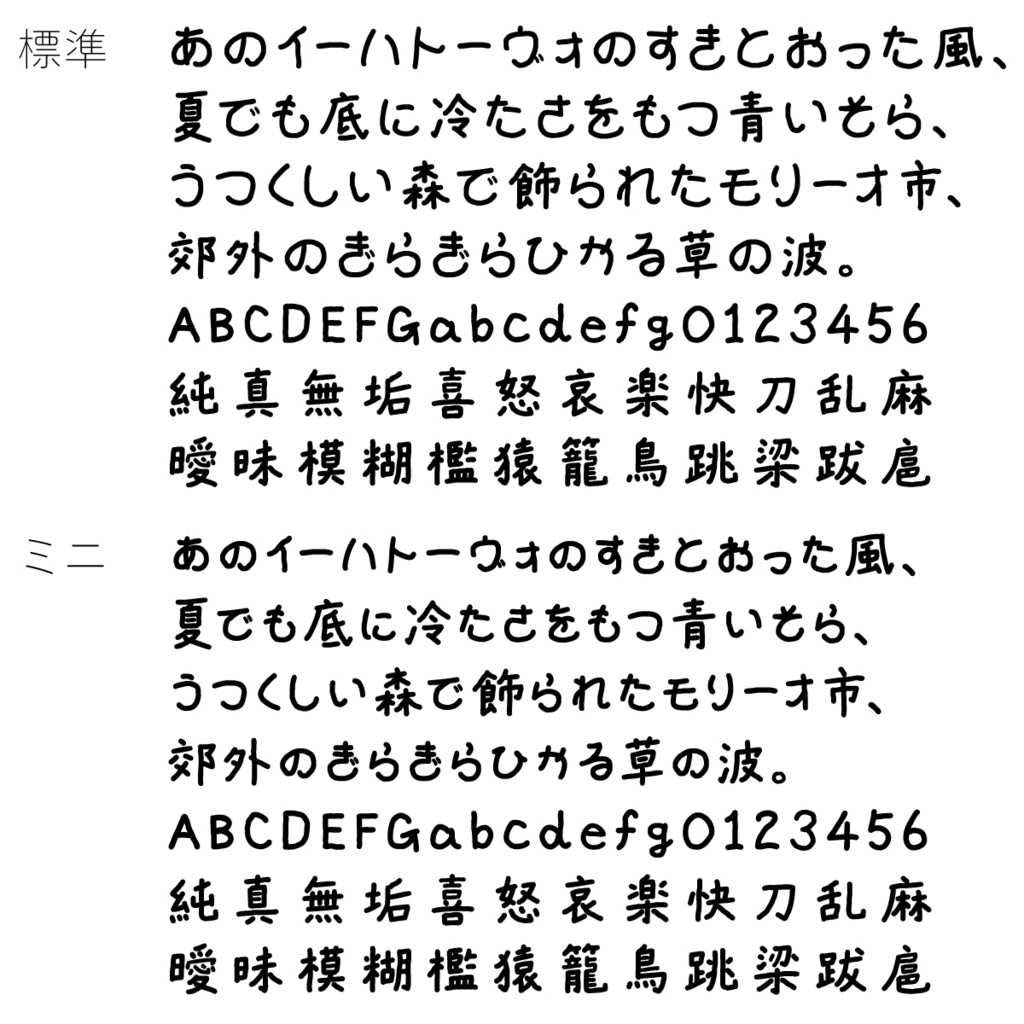
どんなフォント?
TK-takumi書痙フォントよりもユル~いイメージになるよう、仮名文字の中に意識して空間を作り、文字通り“ゆとり”を持たせたフォントです。名前の由来としては、同時に、ゆとり世代であるtakumiが作ったフォントだから、ダサさがゆとり世代っぽい?から、という、自虐的な意味も込めています(笑)。 比較的自由なイメージの手書き風フォントと違い、ちょっぴりデザインフォント寄りのコンセプトで制作しました。TK-takumi書痙フォントと比べるとユルめのかな文字で、今にもコロコロと転がりだしそうなかわいらしさも感じられるデザインになっています。こちらはそんな仮名文字を最大限生かせる、低年齢向けの印刷物や、友達に気楽な気持ちで送る手紙、地域のイベントの案内状など、肩肘張らずにフォントをお使いになりたい時におすすめです。 存在感と説得力のある、漢字とかなの大きさを揃えた通常フォントと、かなが小ぶりで本文でも使いやすく、漢字とのバランスがより良くなった「ミニ」フォントの2種類を用意しております。 また、それぞれに等幅フォントとプロポーショナルフォントがありますので、用途に合わせてお使い頂けます。